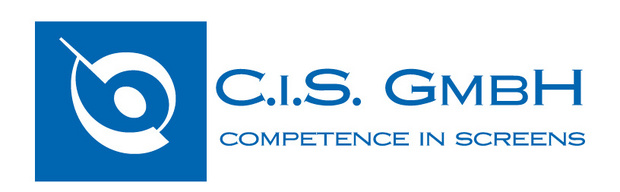
Identifikation einer Logotype (mit Bild)
Kann mir jemand sagen um welche Schrift es sich bei dieser Logotype handelt?
Der Schnitt scheint keine echten Kapitälchen zu beinhalten und die Schrift kommt mir sehr bekannt vor, kann aber trotzdem nicht sagen wie sie heißt.